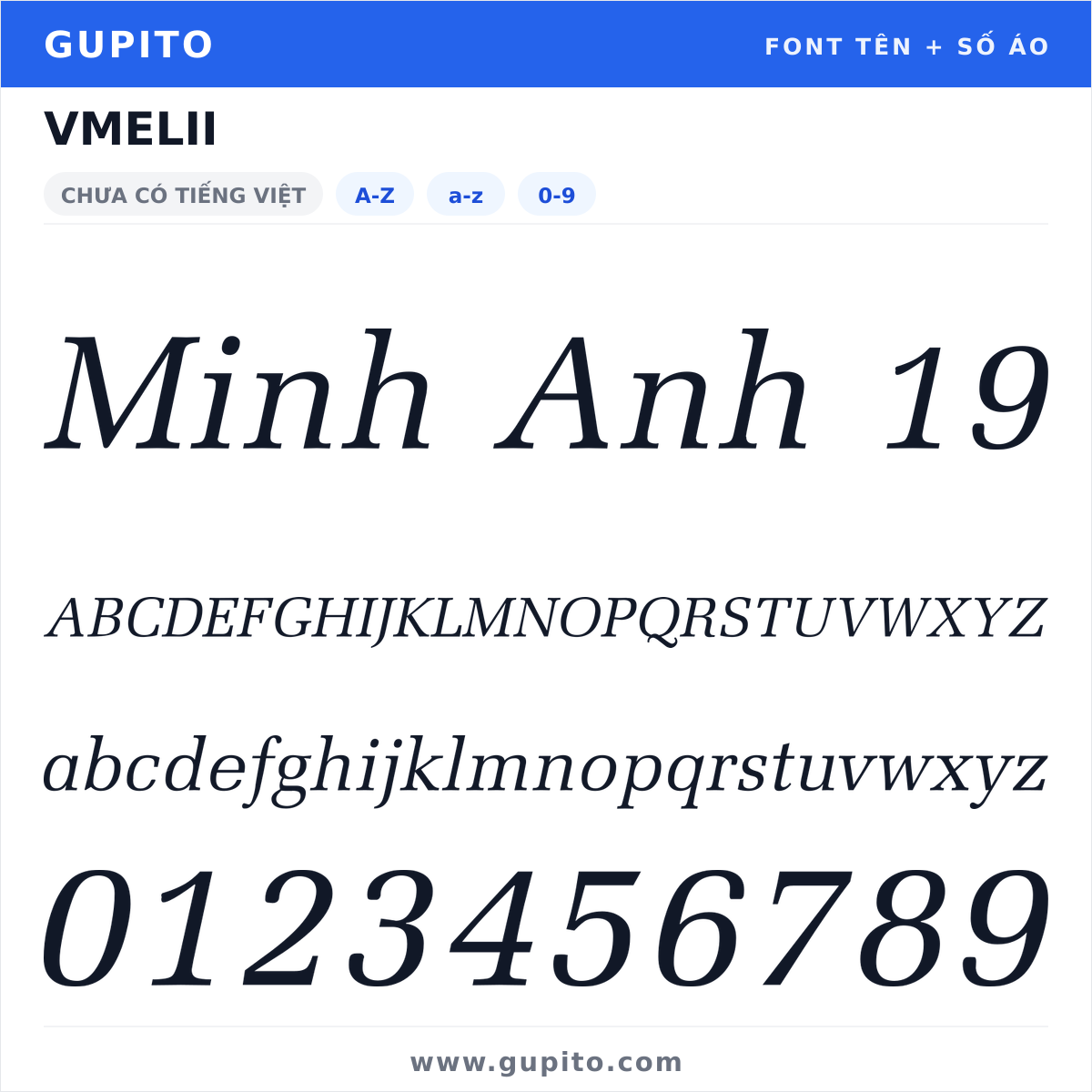
VNI-Meli-Italic
VNI-Meli-Italic · Font VMELII in tên áo, số áo thể thao, chữ in chuyển nhiệt · chữ nghiêng đậm
Font VMELII với nét chữ nghiêng, đậm, chân chữ rõ ràng, có đủ bảng chữ cái và số 0-9, lý tưởng để in tên áo bóng đá, áo lớp, quà tặng. Bộ chữ VNI-Meli-Italic dùng để in chuyển nhiệt lên áo đấu, áo lớp, áo nhóm và đồ thể thao theo yêu cầu. Kiểu dáng: chữ nghiêng đậm. Font dùng cho chữ không dấu và số áo. Có đủ bộ chữ số để in số áo. Từ khoá liên quan: font vmellii, font in ten ao, font in so ao, font the thao, font chuyen nhiet, font a-z, font 0-9, font chu thuong.